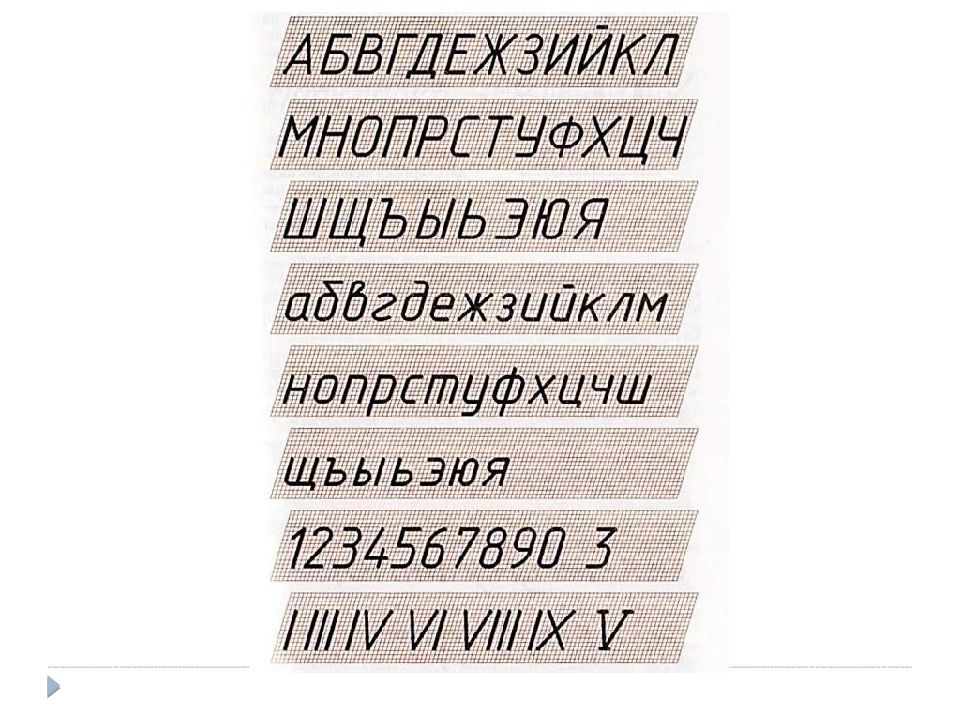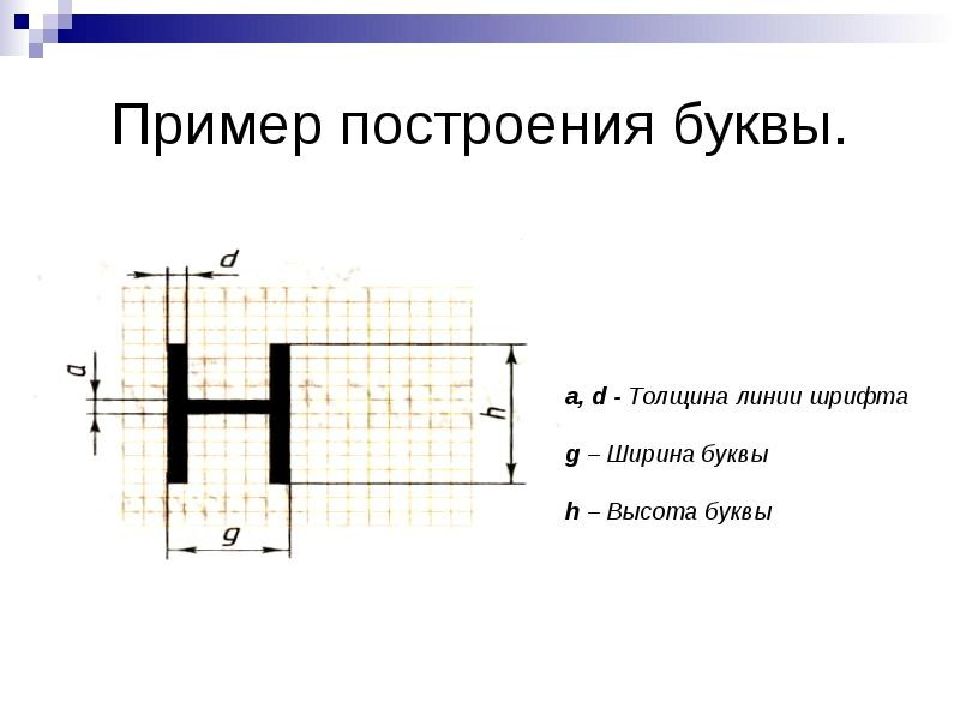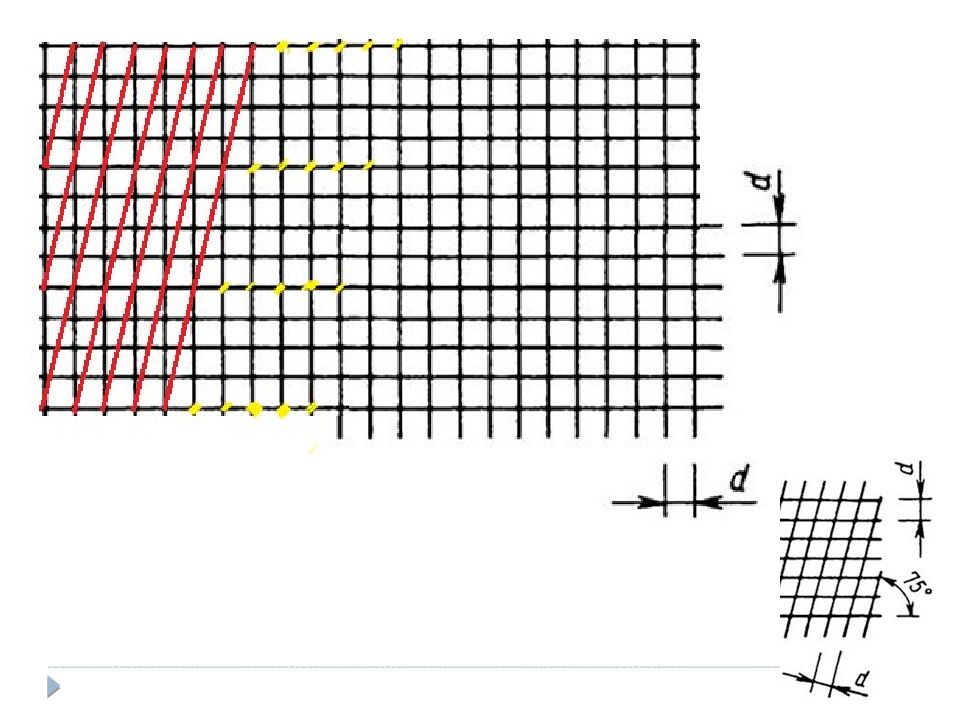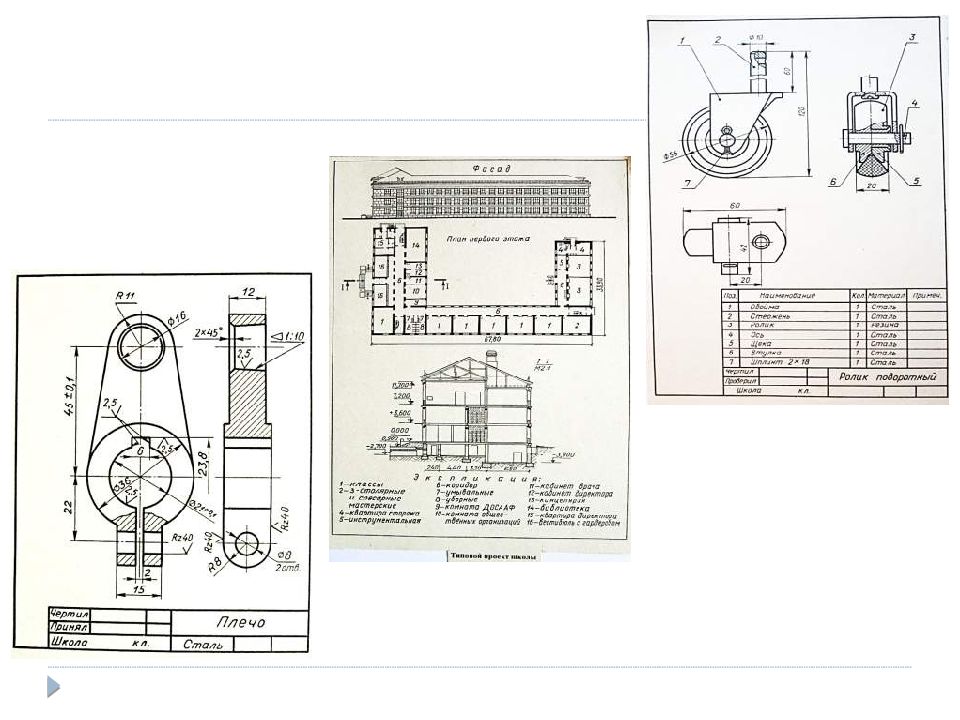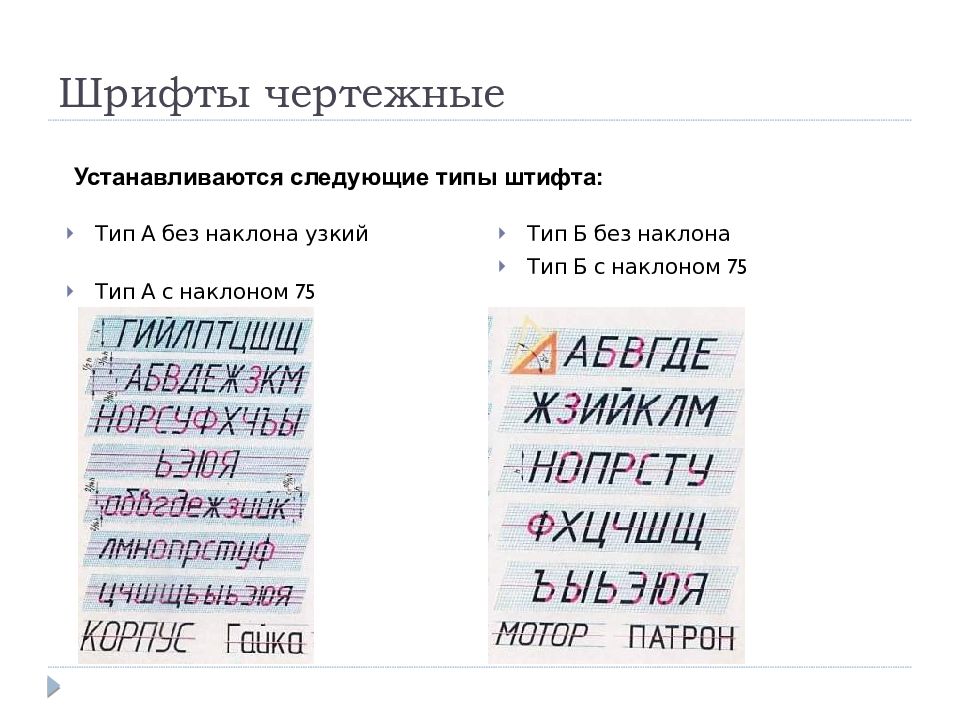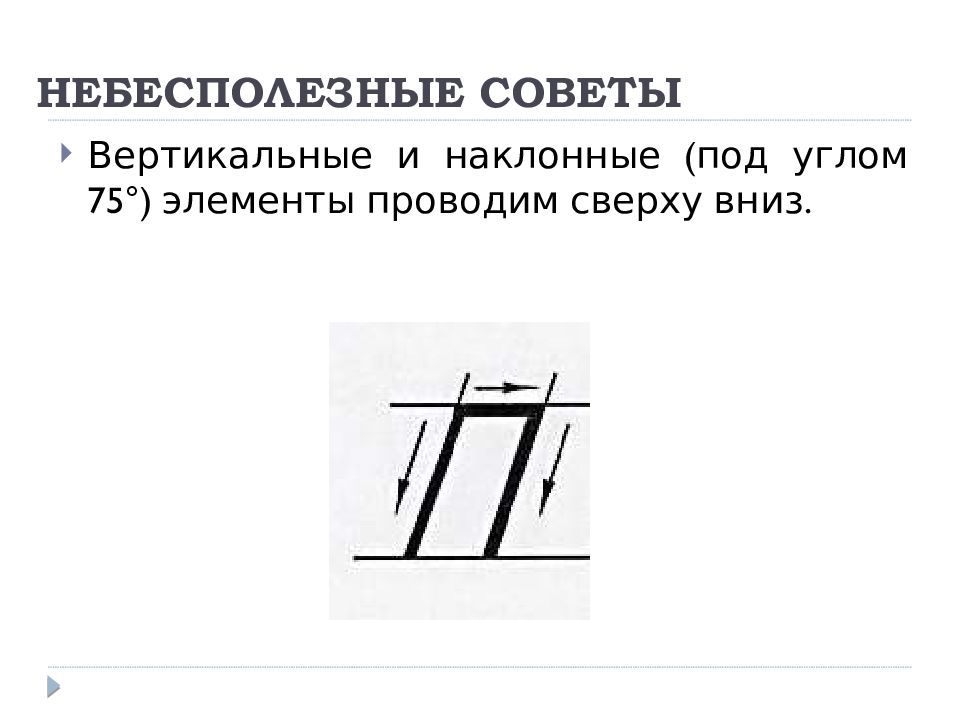
Слайд 3: Шрифты чертежные
Тип А без наклона узкий Тип А с наклоном 75 Тип Б без наклона Тип Б с наклоном 75 Устанавливаются следующие типы штифта: Шрифты чертежные
Слайд 4: ШРИФТ ЧЕРТЕЖНЫЙ ГОСТ 2.304 -81
Все надписи на чертежах должны быть выполнены чертежным шрифтом. Начертание букв и цифр чертежного шрифта устанавливается стандартом. Стандарт определяет высоту и ширину букв и цифр, толщину линий обводки, расстояние между буквами, словами и строчками. Шрифт может быть как с наклоном (около 75°), так и без наклона. Стандарт устанавливает следующие размеры шрифта: 1,8 (не рекомендуется, но допускается); 2,5; 3,5; 5; 7; 10 ; 14; 20; 28; 40.
Слайд 5: ШРИФТ ЧЕРТЕЖНЫЙ ГОСТ 2.304 -81
За размер ( h ) шрифта принимается величина, определяемая высотой прописных (заглавных) букв в миллиметрах. Высота буквы измеряется перпендикулярно к основанию строки. Толщину ( d ) линии шрифта определяют в зависимости от высоты шрифта. Она равна 0,1 h. Высота строчных букв примерно соответствует высоте следующего меньшего размера шрифта. Так, высота строчных букв размера 10 равна 7, размера 7 равна 5 и т. д. Верхние и нижние элементы строчных букв выполняются за счет расстояний между строками и выходят за строку на 3d. Ширина большинства строчных букв равна 5d.
По пропорциям буквы алфавита можно разделить на три группы: узкие, нормальные и широкие. К широким буквам относятся Ж, Ш, М, Ю и др., к узким — Р, В, Г, Е, К, 3. Такие буквы, как Н, П, И, А, Ц, — относятся к средним, нормальным. Обычно при построении шрифта разработку широких и узких букв ведут исходя из пропорций нормальных.
Слайд 14: НЕБЕСПОЛЕЗНЫЕ СОВЕТЫ
Вертикальные и наклонные (под углом 75 ° ) элементы проводим сверху вниз.
Слайд 15: НЕБЕСПОЛЕЗНЫЕ СОВЕТЫ
Если в букве есть скругления, то сначала выполняем скругления, а потом плавно соединяем их прямыми.
Слайд 16: НЕБЕСПОЛЕЗНЫЕ СОВЕТЫ
Для качественного выполнения надписей чертежным шрифтом, сначала размечаем буквы тонкими линиями (мягким карандашом). Карандаш затачивается в зависимости от толщины шрифта (параметра d ).